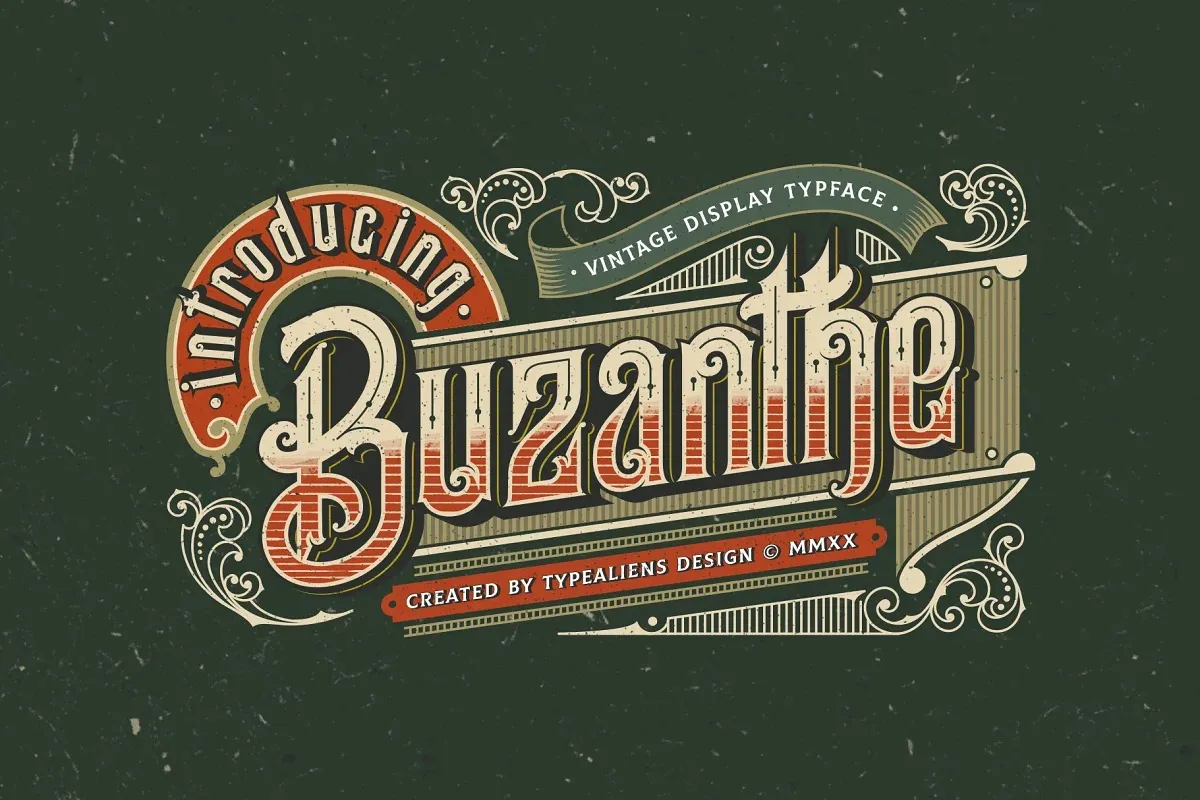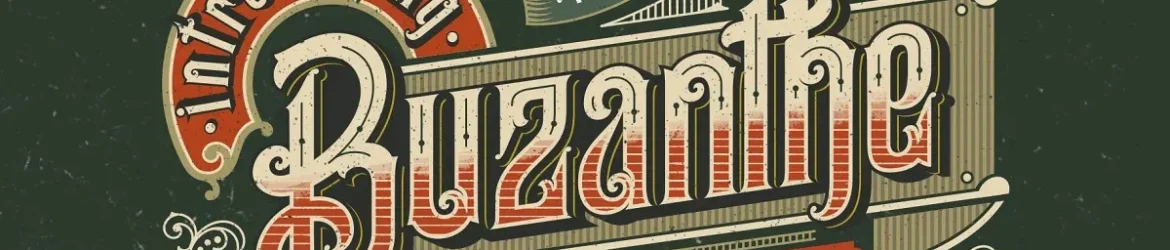
A Buzanthe Font é uma elegante escolha para aqueles que desejam incorporar elementos únicos no design de seus projetos. Inspirada nos Blackletter fonts, ela oferece um toque arrojado e autêntico, com alguns modificadores e ornamentos adicionais. Isso a torna uma fonte de exibição única e encantadora, perfeita para combinar com elementos clássicos como badges ou ilustrações. Esta font é perfeitamente adaptada para quem busca um design gráfico que seja autêntico e chamativo. Com seu conjunto sofisticado de linhas e traços distintos, a Buzanthe traz uma sensação histórica e moderna em cada projeto. Ela não apenas oferece diversão visual, mas também proporciona uma opção diferente para aqueles que desejam um toque único ao usar esta fonte. Se você está procurando por algo que seja mais do que simplesmente uma fonte; algo que se destaque e traga vida a seus projetos, a Buzanthe pode ser o que você precisa. Esse é definitivamente o tipo de elemento gráfico que vai destacar seu trabalho e torná-lo ainda mais memorável.